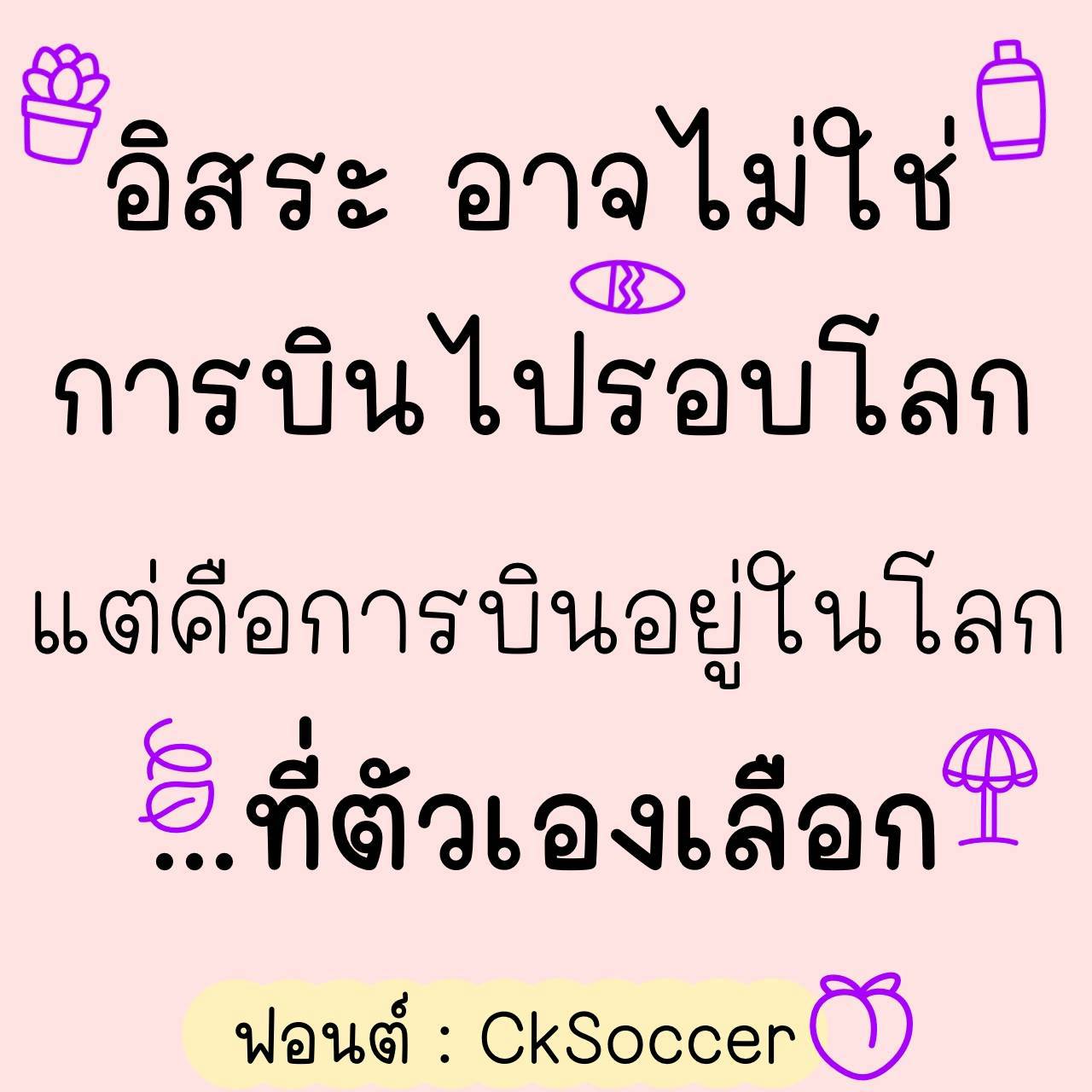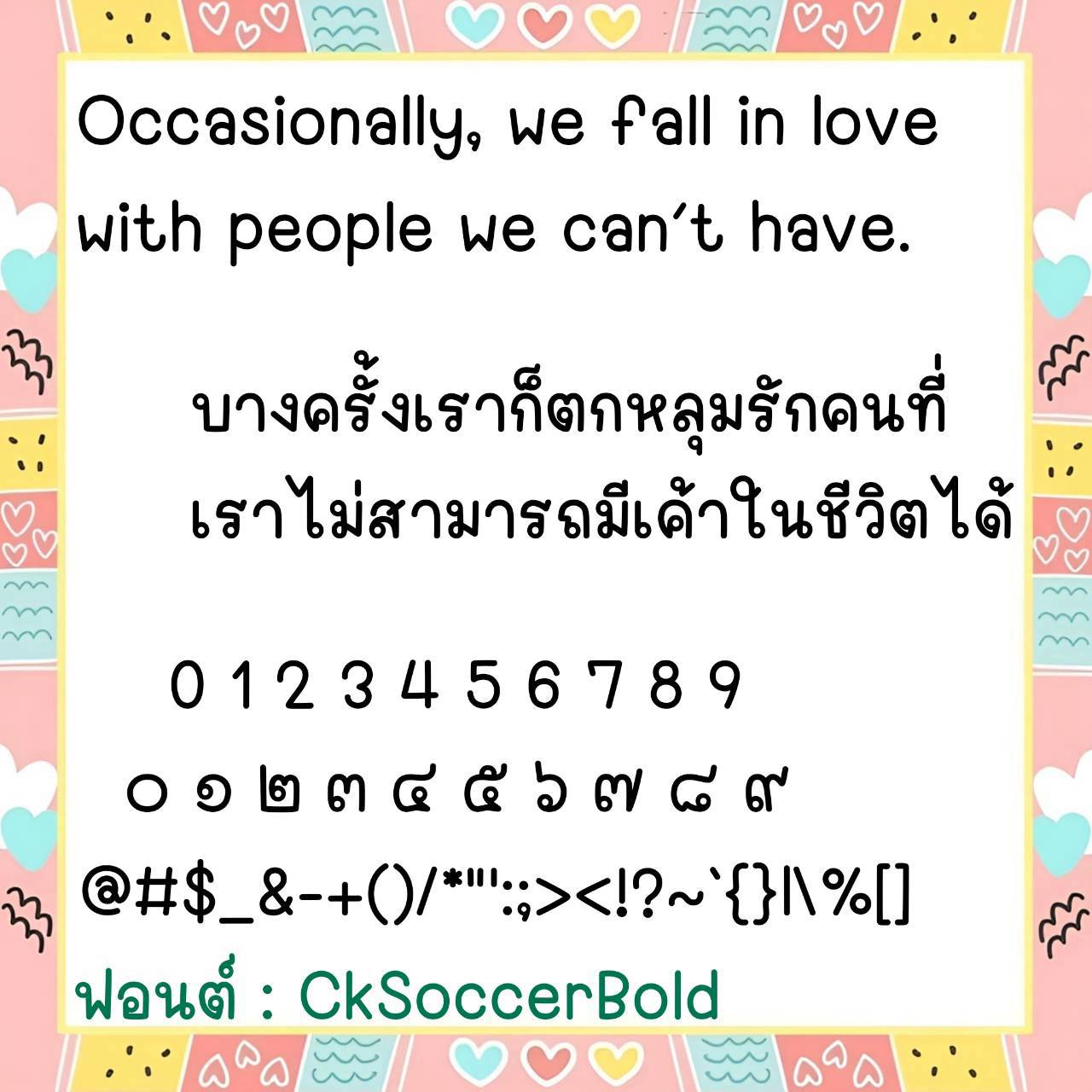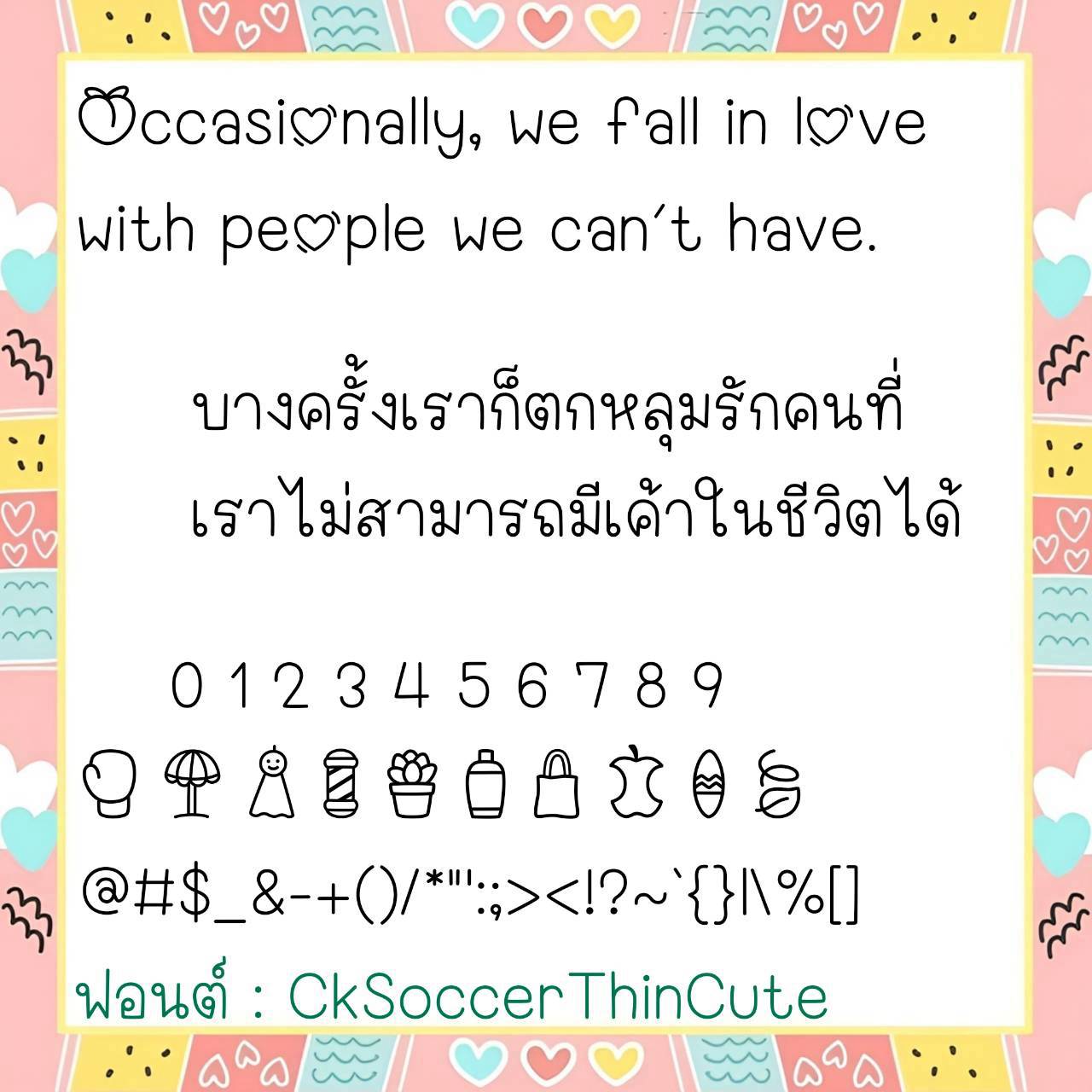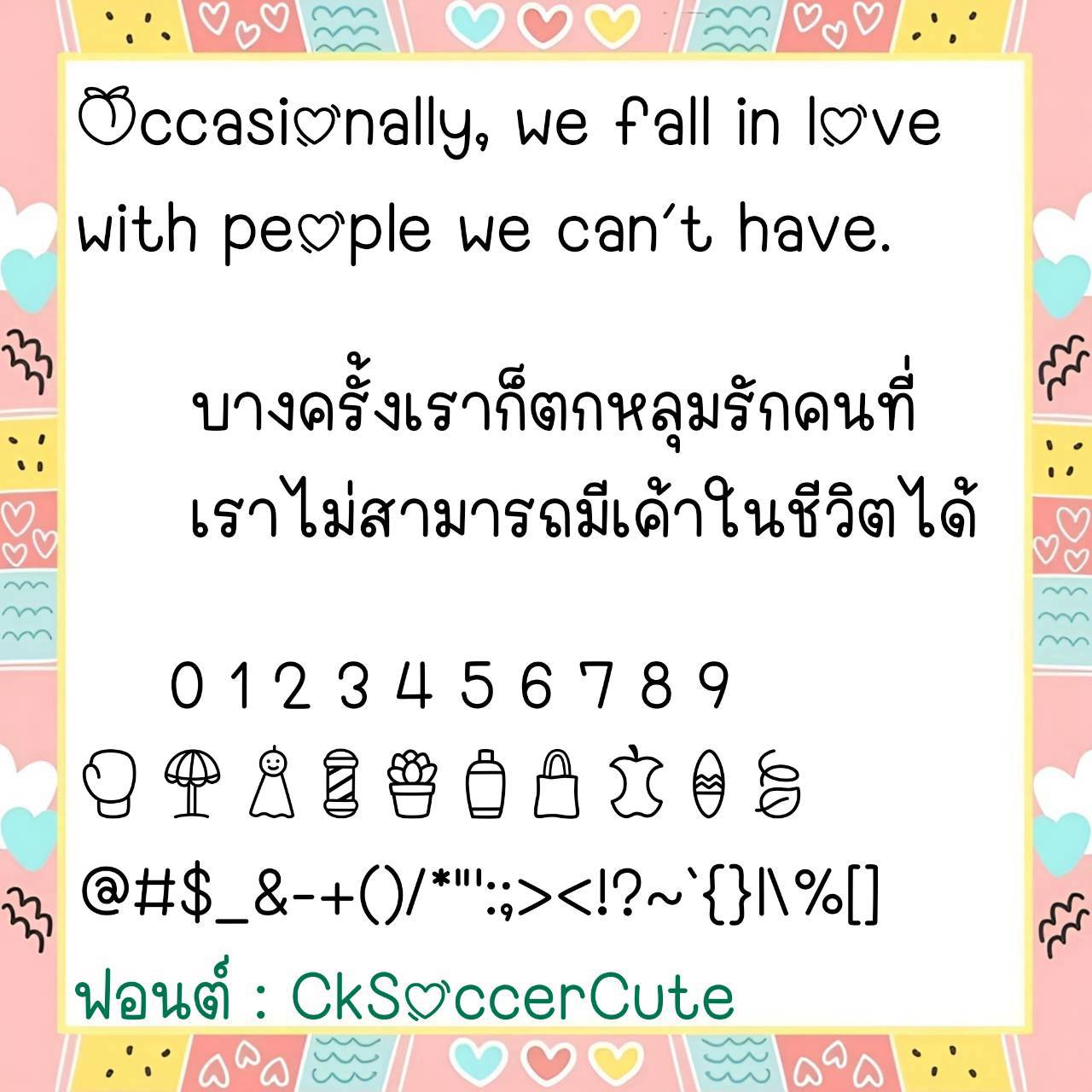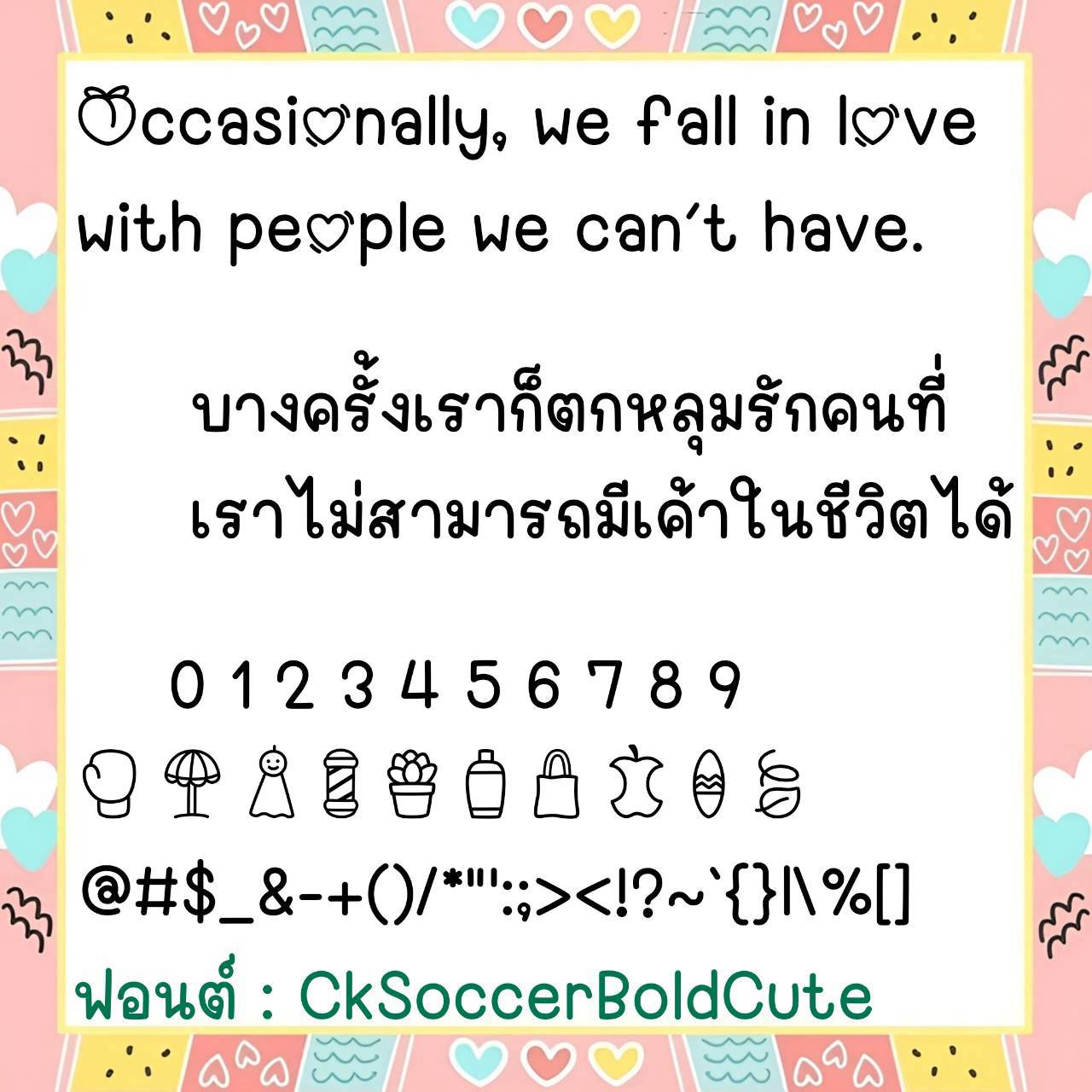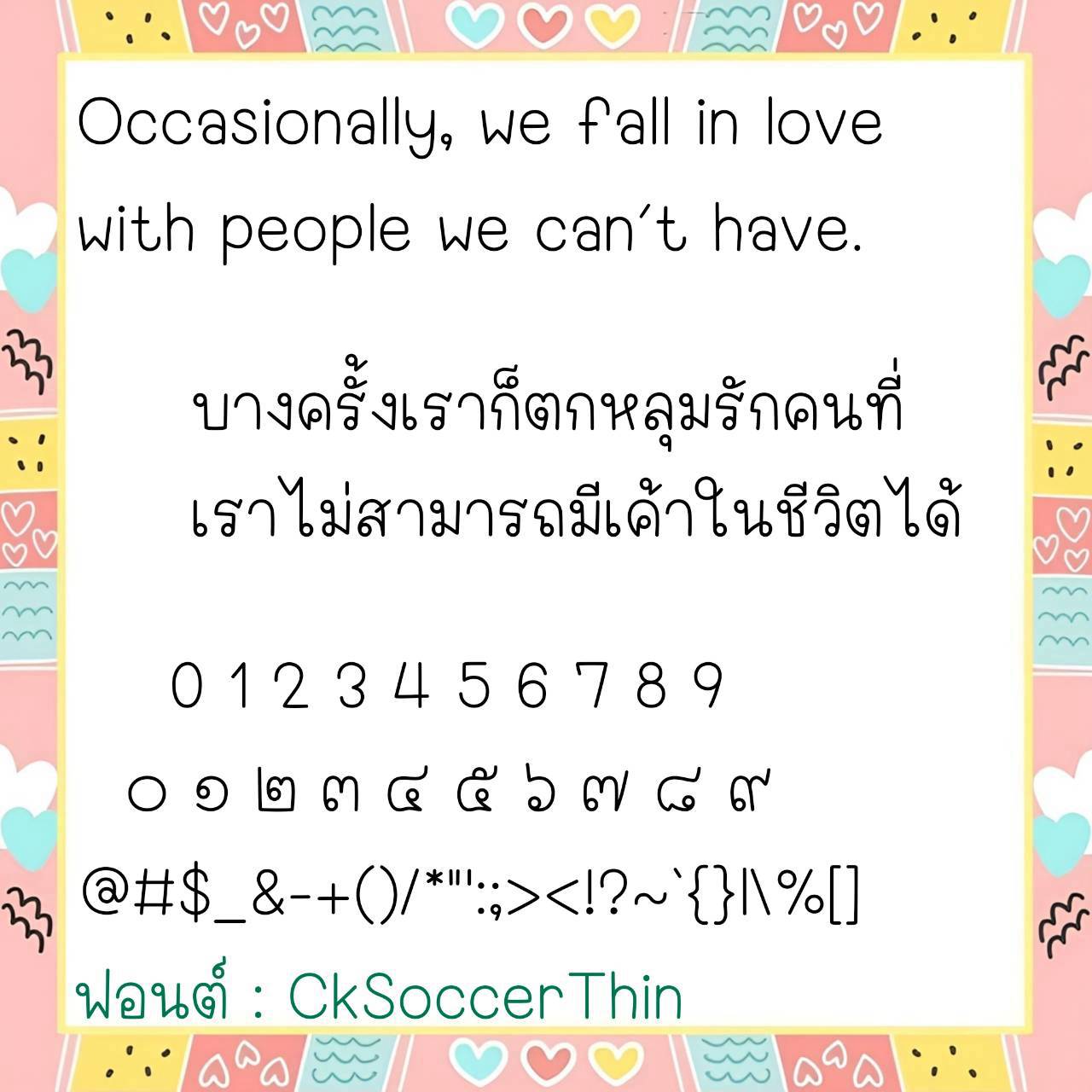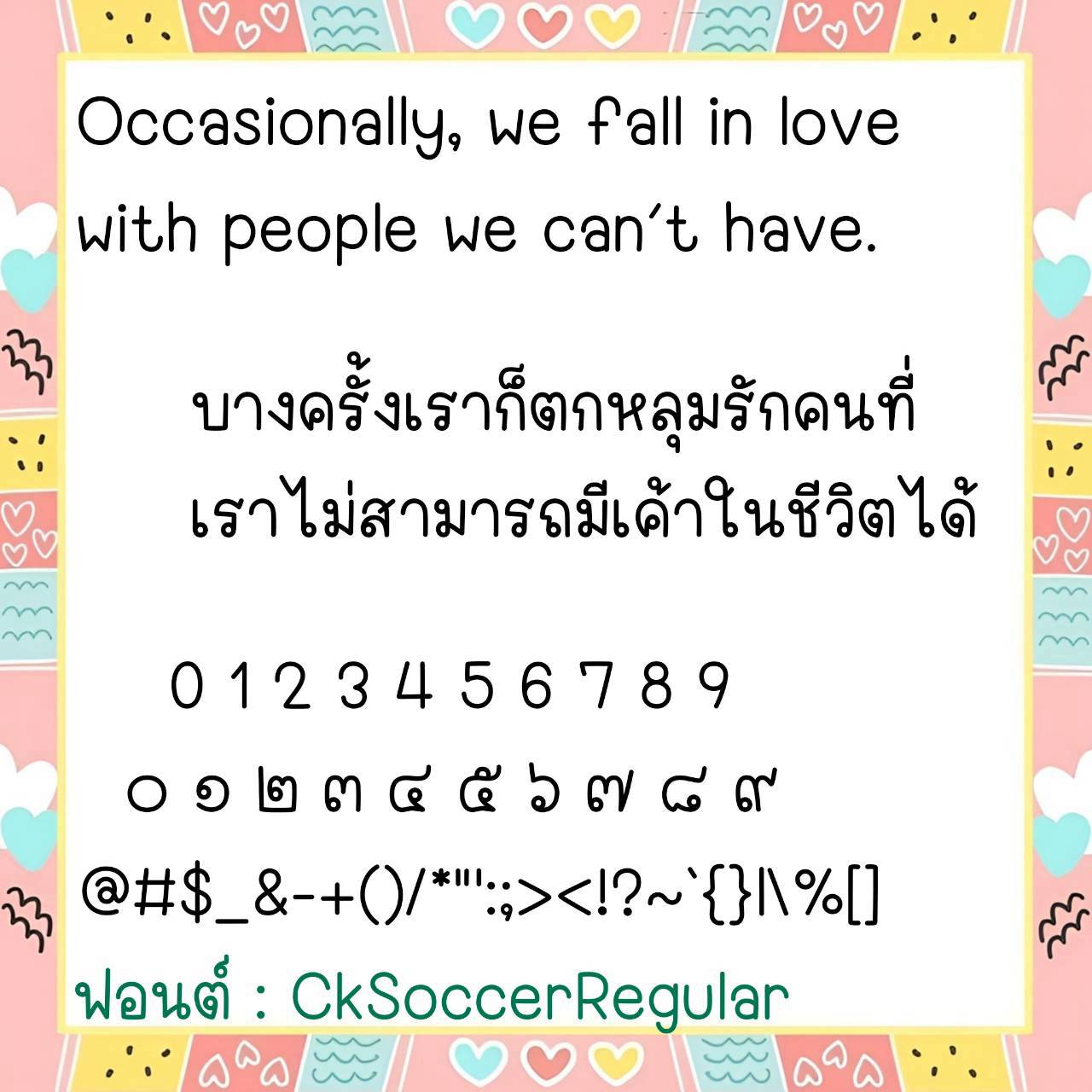
Font CkSoccer
ชื่อสินค้า : Font CkSoccer 💙
🔸 ฟอนต์ลายมือแนวน่ารัก ขนาดตัวกำลังพอดี ดูน่ารักแบบวัยรุ่น เน้นอ่านง่ายสบายตา และยังมีไฟล์อิโมจิน่ารักๆที่ใช้แทนเลขไทยให้ด้วยค่ะ 🥰💙
🔹 A cute handwritten font with a perfect size, ideal for teenagers. It’s easy to read and visually appealing, and includes cute emoji files to replace Thai numerals. 🥰💙